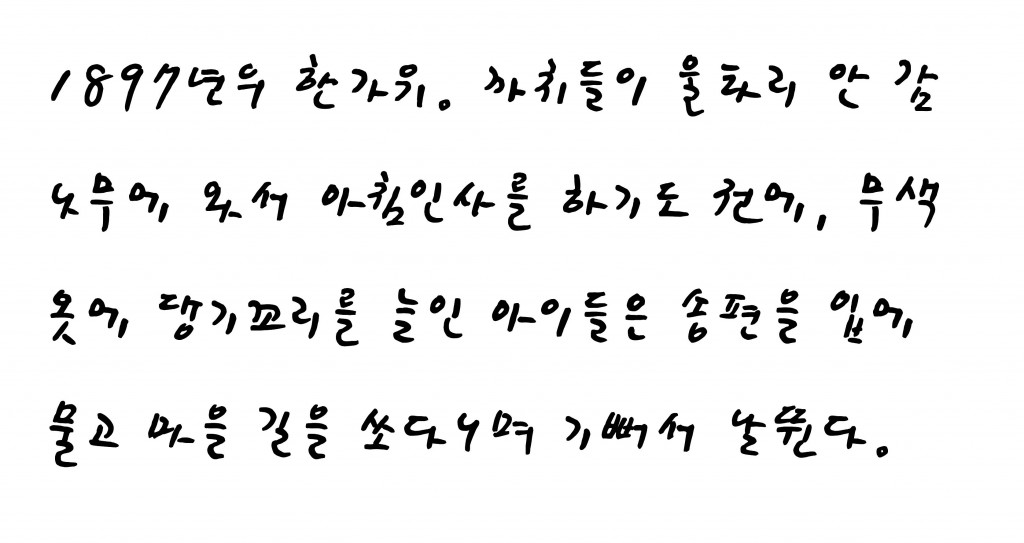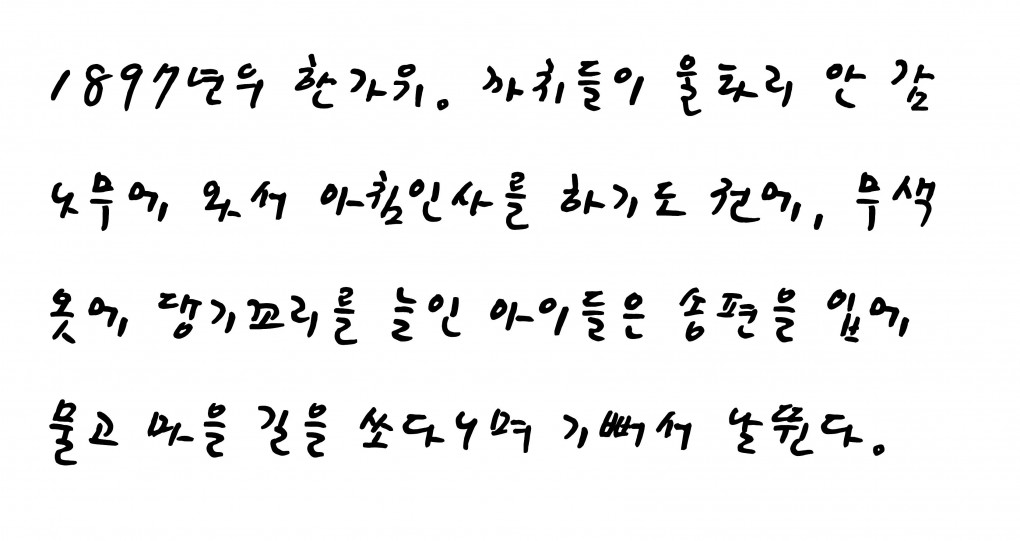
故 박경리 작가의 손글씨, 폰트로 되살아나다
문화체육관광부와 한국저작권위원회가 지난 12월 27일 공유마당을 통해 박경리 작가의 손글씨로 만든 ‘KCC박경리체’를 공개했다.
17년 공개된 KCC김훈체에 이어 이번에 발표된 KCC박경리체는 국민 손글씨 선정 위원회에서 선정했으며, 토지문화재단을 통해 손글씨를 기증받아 제작된 폰트다. 국민 손글씨 선정 위원회는 누구나 자유롭게 이용이 가능한 폰트 발굴을 위해 문화계, 예술계, 저작권 전문가 등 총 6명으로 구성되어 폰트 제작 후보자가 될 저명인사들을 선별 후 손글씨를 기증받아 제작한다.
대하소설 <토지>로 잘 알려진 故 박경리 작가는 한국 근·현대사를 누구보다 깊고 섬세하게 다룬 소설가다. 토지문화재단의 김영주 이사장은 “국민들이 박경리 작가의 숨결을 느낄 수 있도록 글씨체가 훼손되지 않고 그대로 복원된 것 같다”며 “올해는 박경리 작가 추모 10주기인데 KCC박경리체가 제작, 배포되어 국민들이 박경리 작가의 문학세계에 공감하고 이를 잊지 않았으면 한다”고 소감을 밝혔다.